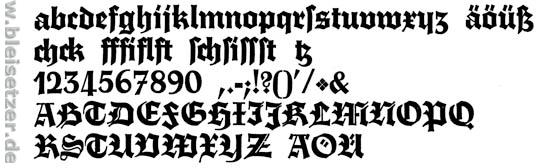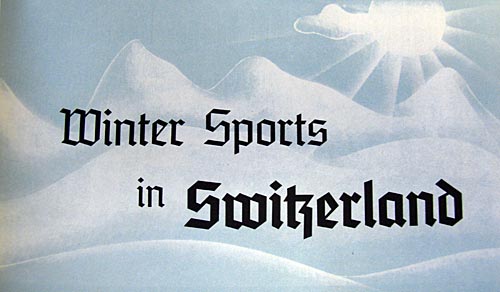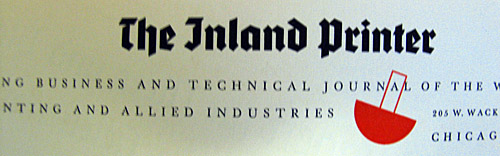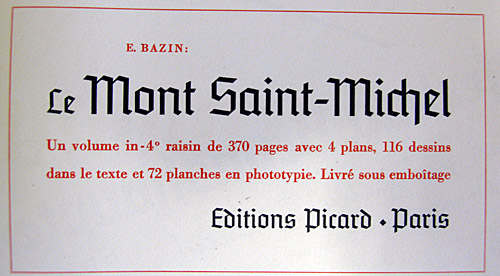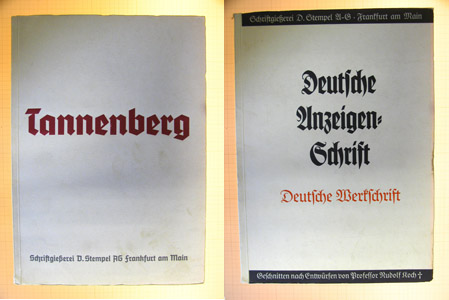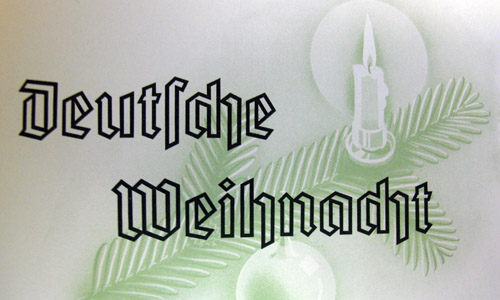
Schaftstiefelgrotesk?
Die Tannenberg bedeutet Fortschritt
Die Tannenberg setzt die Linie des gotischen Schriftstils, in dem Gutenberg und Dürer Hochformen geschaffen haben, in unserer Zeit fort. Mit der eigentlichen Fraktur im engeren Sinne, die dem freien Schreibzeug das Wesen ihres Stiles verdankt, kann die Tannenberg nicht in Zusammenhang gebracht werden. Sie knüpft vielmehr an die in ihrem Grundaufbau konstruktive Schrift der Gotik an. Wir wollten sie gotische Schrift des hohen Mittelalters, die mit ihrer Strenge und Straffheit dem Empfinden unserer Zeit entgegenkommt, aus dem Wollen, dem Geiste, den Anschauungen unserer Tage weiter entwickeln und neu darstellen und unserer Gegenwart ein in deutscher Überlieferung beruhendes, wesensverwandtes Ausdrucksmittel zur Verfügung stellen. Das ist die Grundabsicht, die zur Schaffung der Tanneberg geführt hat. Das dieses Wollen verstanden worden ist und unmittelbar Anklang gefunden hat, beweist ihr großer Erfolg. Es ist nicht so, daß erst der Sinn und das Verständnis für die Formenwelt dieser Schrift hätten geweckt werden müssen, der Boden für ihre Aufnahme war vielmehr gelockert und bereitet. Sie ist von Anfang an mit einer Freudigkeit er Zustimmung und Sicherheit des Urteils aufgenommen worden, die zeigen, daß die Tannenberg als der besonders gelungene Ausdruck neuen deutschen Formwillens empfunden wird.
Die Tannberg ist neues Leben auf altem Grunde, und weil sie Altes und Neues in sich zu geschlossenem Ausdruck bringt, weil sie so vollendet geformt ist, ist sie als Zeichen der Zeit verstanden und in ausgedehnte Verwendung genommen worden. Wo sie eingesetzt wird, geht von ihr die Überzeugung aus:
Das ist die schöne neudeutsche Schrift.
was ich nicht wusste:
es gab auch einen lichten schnitt der tannenberg. :shock:
und was ich soben entdeckt habe:
die tannenberg wirkt in fremdsprachen regelrecht harmlos.
mehr (wie immer schlecht geknippste) bilder aus dem tannenbergmuster
und dem deutsche anzeigenschrift/deutsche werkschrift schriftmuster gibts
hier nochmal die lichte tannenberg:
Ich muss das jetzt einfach ’mal gegenüberstellen!
Albert Kapr schreibt: Die schlichte Gotisch stehe für Gewalttätigkeit schlechthin und zitiert Willberg: „die aufs Einfachste reduzierte Form,
die der Setzervolksmund schon in den dreißiger Jahren „Schaftstiefelgrotesk“genannt hatte
– präziser geht es nicht, diese Formen sollten sich zur Fraktur so verhalten, wie die Grotesk zur Antiqua,
und das Ergebnis waren Zeilen von marschritthafter Härte.“
... Brutale Vergröberung der Form (durch den Vergleich zweier Schriften,
die beide in den dreißiger Jahren entstanden, besser verständlich, als durch Beschreibung) ... “.
(in Albert Kapr: Form und Geschichte der gebrochenen Schriften)
Welche zwei Schriften meint er?
An anderer Stelle wirft Willberg der Frakturgrotesk „die formal reduzierte, vereinfachte,
man möchte sagen brutalisierte Form“ als „das verkitschte Pathos der Nazi-Ästhetik“ vor.
(hier zitiert nach S. Wehde, Typographische Kultur, Tübingen 2000)
Und Kapr schreibt:
Allein durch die Form „ ... mit primitiver Einfallslosigkeit die Figuren gleichgestaltet ...
die Konturen vieler Figuren schienen mit dem Lineal gezogen. Ihre Formen widerspiegelten
den Gleichschritt und die Disziplin ... “
Schade, dass sich das nicht mehr aufdröseln lässt, wer was wie zu welcher Schrift genau gesagt hat. Das wäre bestimmt ein gutes Thema für eine wissenschaftliche Untersuchung, wie es zu der Abstempelung der gebrochenen Grotesk zur Nazi-Schrift kam und dann bedenkenlos auf alle gebrochenen Schriften übertragen wurde.
Im Forum fiel mal der bezeichnende Satz von jemand der lehrend mit Typografie zu tun hat, „ ... Mein Kollege meinte nun, es müsse unsere Aufgabe sein, die Blackletters wieder auf ihre teils humanistischen Wurzeln zurückzuführen bzw. diese bewusst zu machen, während ich persönlich der Ansicht war, diese Chance sei für immer vergeben.“
Ich möchte zu Willbergs Verteidigung hinzufügen, dass er Typolemik/Typophile (2000, Hermann Schmidt Verlag) seine Meinung über die Schaftstiefelgrotesken revidiert.
@ Stevo: Für Dein historisierendes Bauchredner-Plakat hast Du Dir ja ein besonders übles Plakat als Vorlage ausgesucht …
Die Geheime Staatspolizei (Gestapo) in Düsseldorf hat die Tannenberg für die Formblätter ihrer Aktenvermerke verwendet. Ich hatte heute in anderem als typographischem Zusammenhang einen solchen Aktenvermerk in Händen.
Die Drucksachen wurden damals lokal im jeweiligen Gau für alle Behörden einheitlich gedruckt. Zum Vergleich: Es gab nach 1933 zunächst 33, später 43 Gaue in Deutschland.